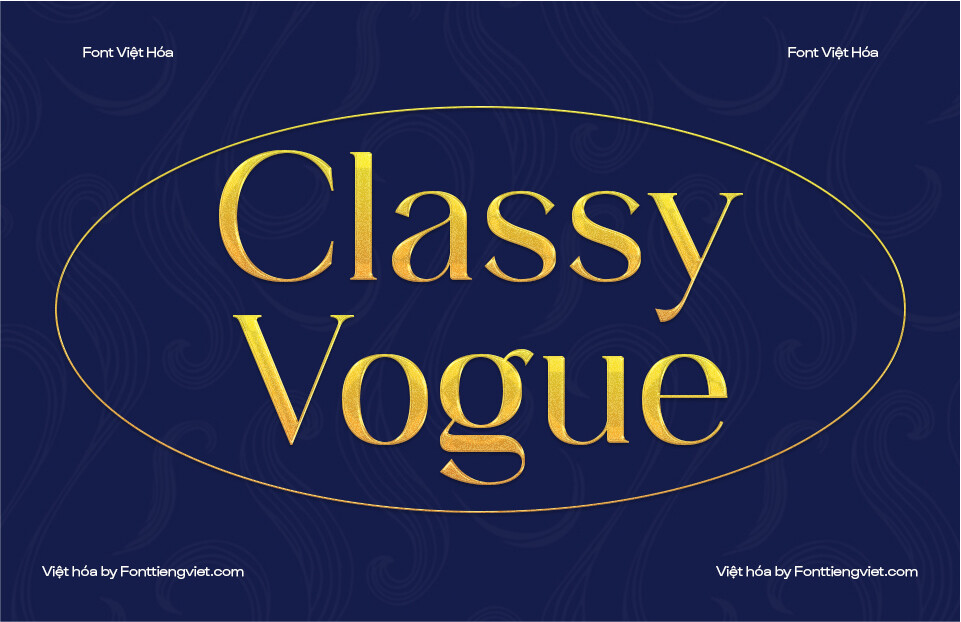
Font Việt hóa 1FTV VIP Classy Vogue
Font Việt hóa 1FTV VIP Classy Vogue: Đẳng cấp thiết kế thời thượng cho dự án sáng tạo
Giới thiệu về Font Việt hóa 1FTV VIP Classy Vogue
Trong thế giới thiết kế đồ họa hiện đại, việc lựa chọn một bộ Font Miễn Phí chất lượng đóng vai trò then chốt để tạo nên linh hồn cho tác phẩm. Font Việt hóa 1FTV VIP Classy Vogue là sự kết hợp hoàn hảo giữa nét cổ điển quý phái và tinh thần hiện đại của các tạp chí thời trang danh tiếng. Được tinh chỉnh kỹ lưỡng với đầy đủ dấu tiếng Việt, bộ font này mang đến sự mượt mà và tính ứng dụng cao cho người dùng tại Việt Nam. Với những đường nét mảnh mai nhưng sắc sảo, nó không chỉ là một công cụ truyền tải thông tin mà còn là biểu tượng của sự sang trọng và phong cách chuyên nghiệp trong mọi bản thiết kế.
Đặc điểm nổi bật của bộ font chữ VIP
Đặc trưng lớn nhất của Font Việt hóa 1FTV VIP Classy Vogue nằm ở độ tương phản cực cao giữa các nét thanh và nét đậm. Đây là phong cách Serif điển hình thường thấy trên bìa các tạp chí hàng đầu thế giới như Vogue hay Harper’s Bazaar. Các ký tự được thiết kế với khoảng cách chuẩn xác, giúp bố cục chữ trở nên thoáng đãng và dễ đọc ngay cả ở kích thước nhỏ. Đặc biệt, bộ font này đã được tối ưu hóa hiển thị cho cả môi trường in ấn lẫn kỹ thuật số, đảm bảo độ sắc nét tuyệt đối khi trình chiếu trên các thiết bị di động hay máy tính.
Ứng dụng Font Việt hóa 1FTV VIP Classy Vogue trong thực tế
Nhờ vẻ ngoài thanh lịch, Font Việt hóa 1FTV VIP Classy Vogue trở thành lựa chọn hàng đầu cho các dự án thiết kế thương hiệu cao cấp. Bạn có thể dễ dàng bắt gặp bộ font này trong các thiết kế logo mỹ phẩm, thiệp mời đám cưới sang trọng hoặc các banner quảng cáo thời trang. Trong môi trường học đường, các bạn học sinh sinh viên cũng có thể sử dụng font chữ này để trang trí slide thuyết trình hoặc làm tiêu đề cho các báo cáo sáng tạo, giúp bài làm trở nên thu hút và chuyên nghiệp hơn hẳn các bộ font mặc định thông thường.
Cách phối hợp font chữ hiệu quả
Để phát huy tối đa vẻ đẹp của Font Việt hóa 1FTV VIP Classy Vogue, các nhà thiết kế thường kết hợp nó với một font chữ không chân (Sans Serif) đơn giản cho phần nội dung văn bản. Sự tương phản giữa nét điệu đà của tiêu đề Classy Vogue và nét hiện đại của phần thân bài sẽ tạo nên một tổng thể hài hòa và tinh tế. Ngoài ra, việc sử dụng các gam màu trung tính như đen, trắng, vàng gold sẽ càng làm tôn lên vẻ quý tộc vốn có của bộ font đặc biệt này trong các ấn phẩm đồ họa.
Lợi ích khi sử dụng font chữ đã Việt hóa
Việc sử dụng Font Việt hóa 1FTV VIP Classy Vogue giúp loại bỏ hoàn toàn nỗi lo về lỗi font hay nhảy ký tự khi gõ tiếng Việt. Đây là ưu điểm lớn nhất dành cho các designer Việt Nam, giúp tiết kiệm thời gian chỉnh sửa và đảm bảo tính thẩm mỹ đồng nhất cho toàn bộ văn bản. Bạn có thể tự tin sáng tạo những câu slogan hay đoạn trích dẫn giàu cảm xúc mà không cần phải can thiệp thủ công vào từng dấu câu, từ đó nâng cao hiệu suất làm việc một cách đáng kể.
Tóm lại, Font Việt hóa 1FTV VIP Classy Vogue là một tài nguyên quý giá cho bất kỳ ai đang tìm kiếm sự khác biệt và đẳng cấp trong thiết kế. Với khả năng tương thích tốt và vẻ đẹp vượt thời gian, bộ font này chắc chắn sẽ làm hài lòng ngay cả những người dùng khó tính nhất. Hãy truy cập ngay kho dữ liệu của chúng tôi để khám phá thêm nhiều bộ Font Miễn Phí, Font Việt Hóa, Font Việt hóa 1FTV VIP Classy Vogue độc đáo khác nhằm làm phong phú thêm thư viện sáng tạo của bạn. Chúc các bạn có những tác phẩm thiết kế ấn tượng và đầy cảm hứng với bộ font chữ đẳng cấp này.